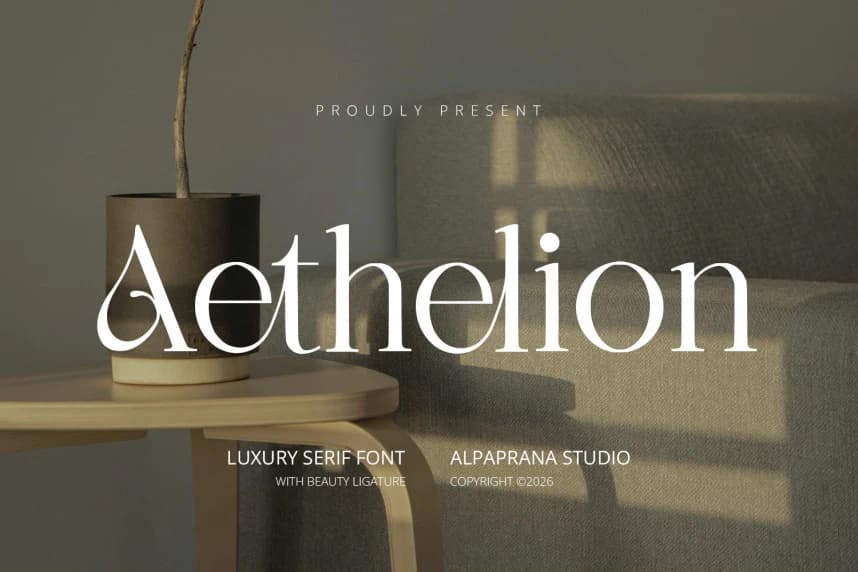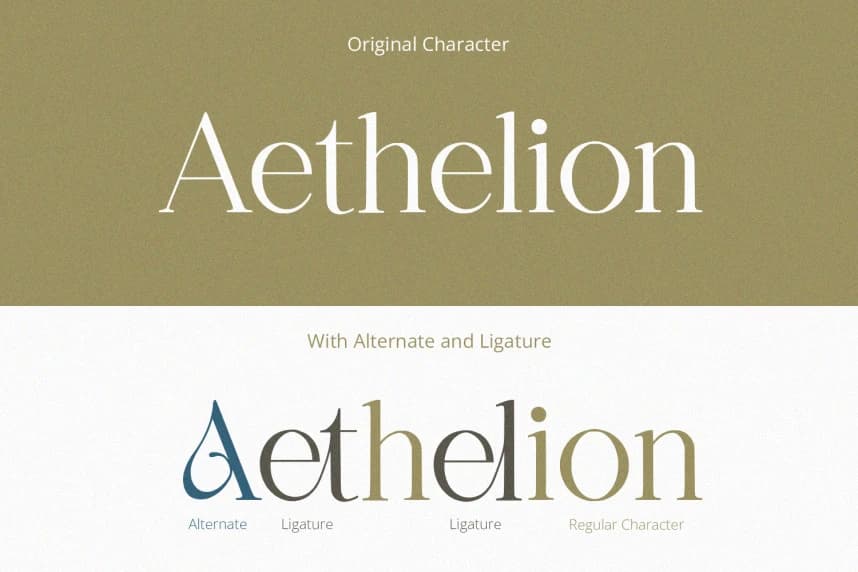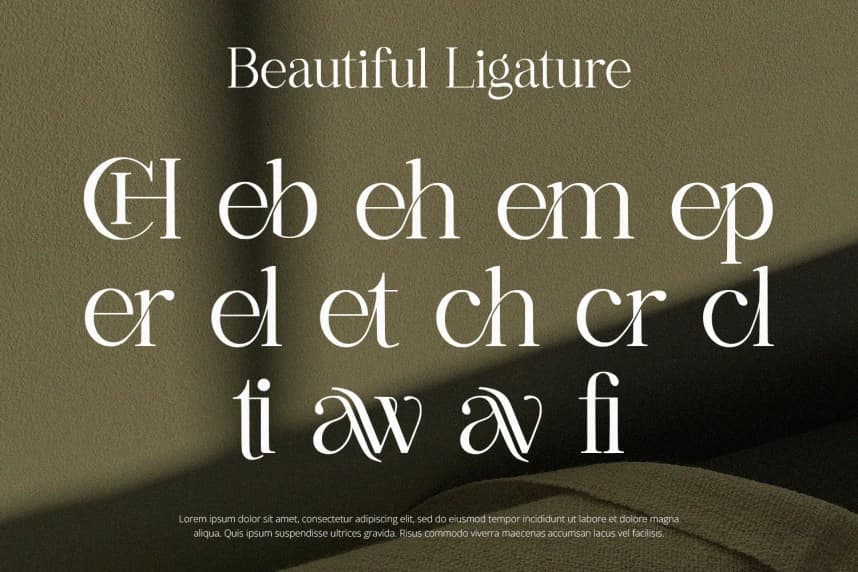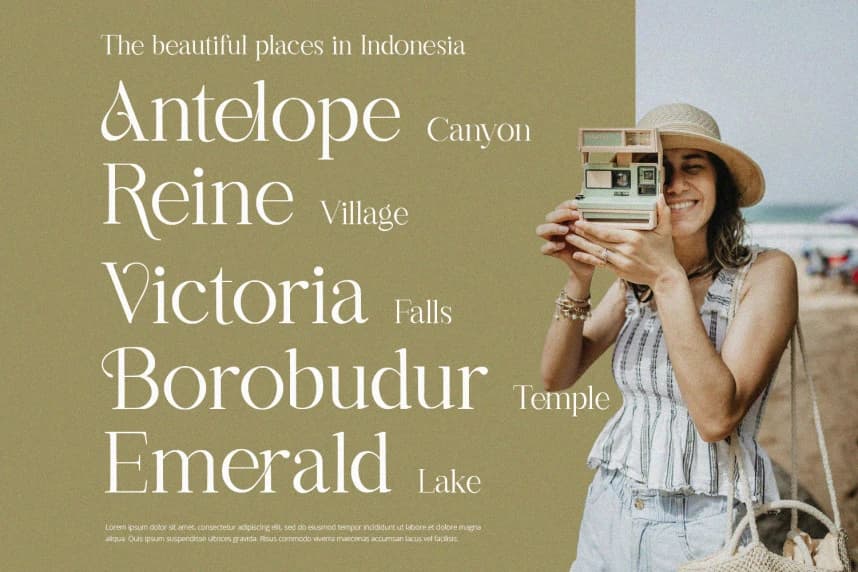
Aethelion Serif Font, modern görünümlü bir serif fontudur. Markalaşma, Logo Tasarımı, Lettering, Logotip, Giyim, Poster, Dergi, Ambalaj, Posterler, Alışveriş Çantaları, Tişörtler, Kitap Kapakları, Fotoğrafçılık, Özel Etkinlikler ve diğer tasarım projeleri için mükemmel bir şekilde kullanılabilir.
Aethelion Serif Font, modern hissi veren bir serif yazı tipidir. Markalaşma için mükemmel bir şekilde kullanılacaktır; Logo Tasarımı, Harf Tasarımı, Logotip Tasarımı, Giyim, Afiş, dergi, ambalaj, afişler, alışveriş çantaları, tişörtler, kitap kapakları, fotoğrafçılık, özel etkinlikler ve diğer tasarım projeleri için.